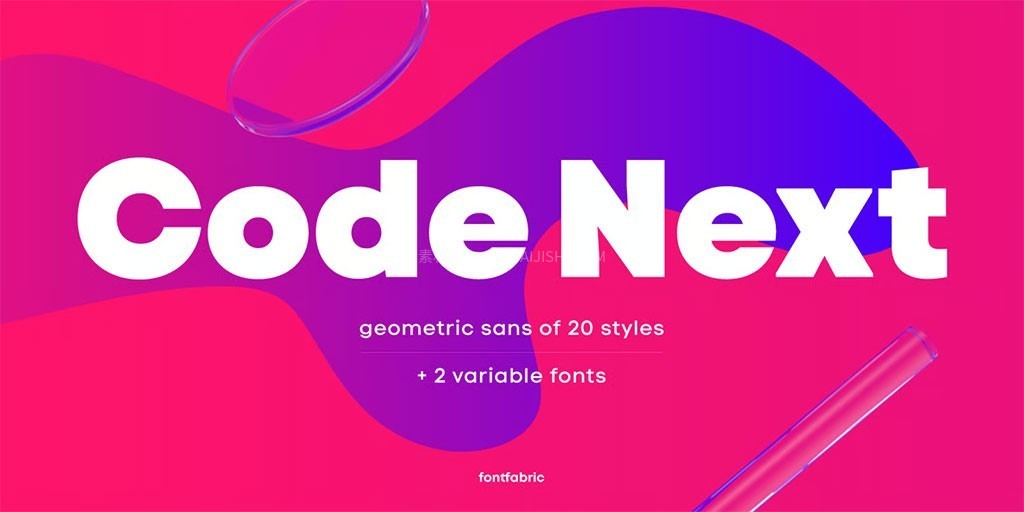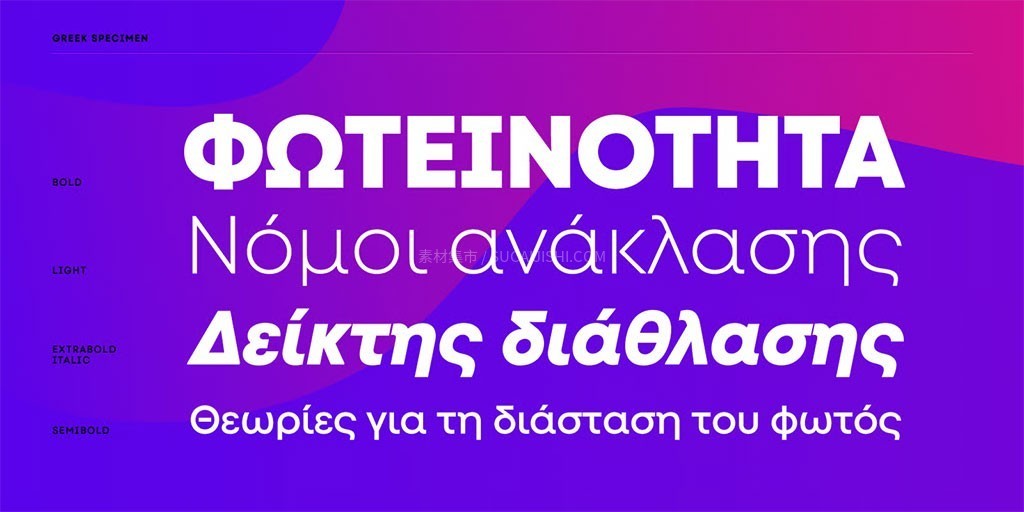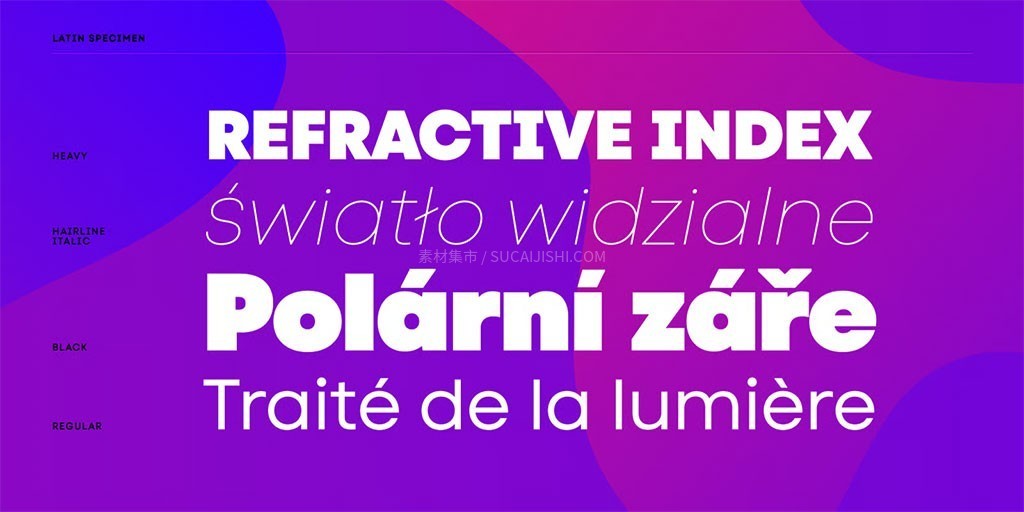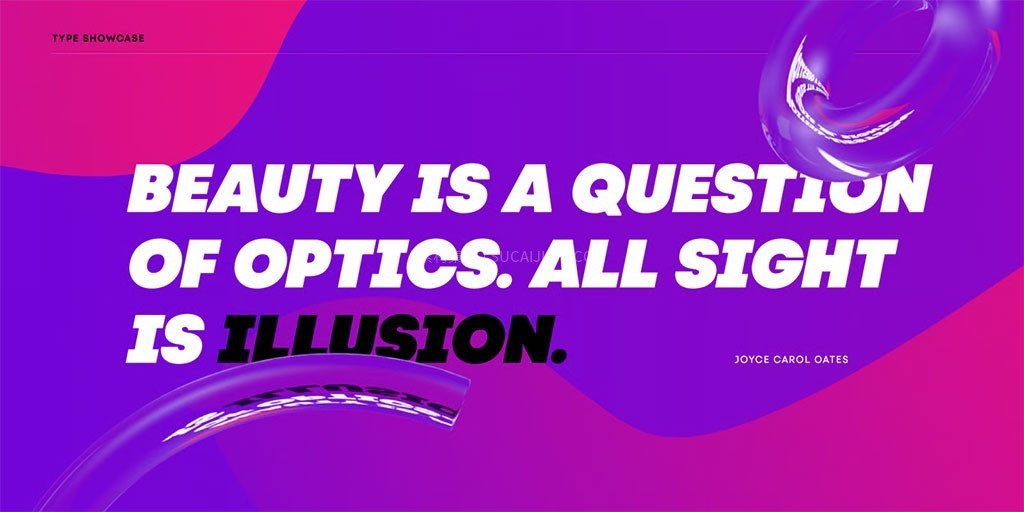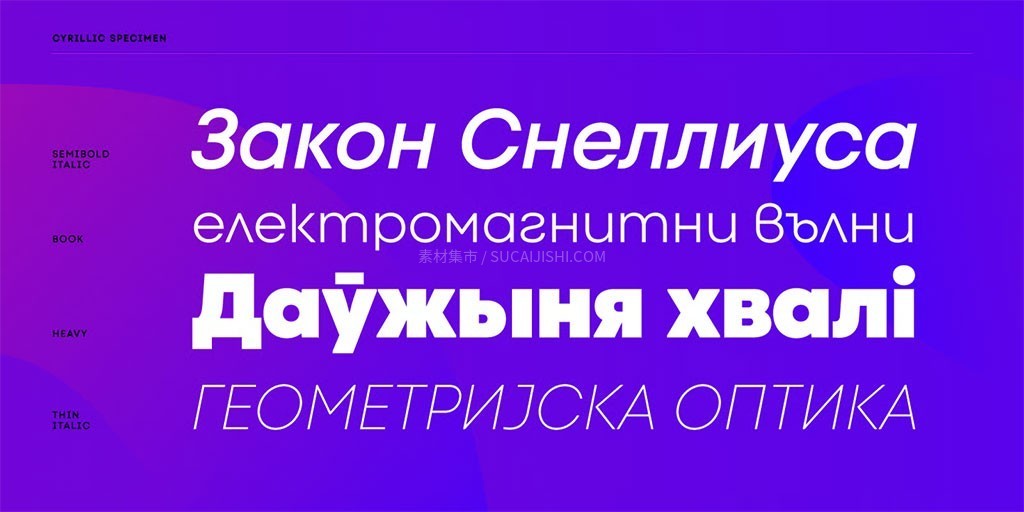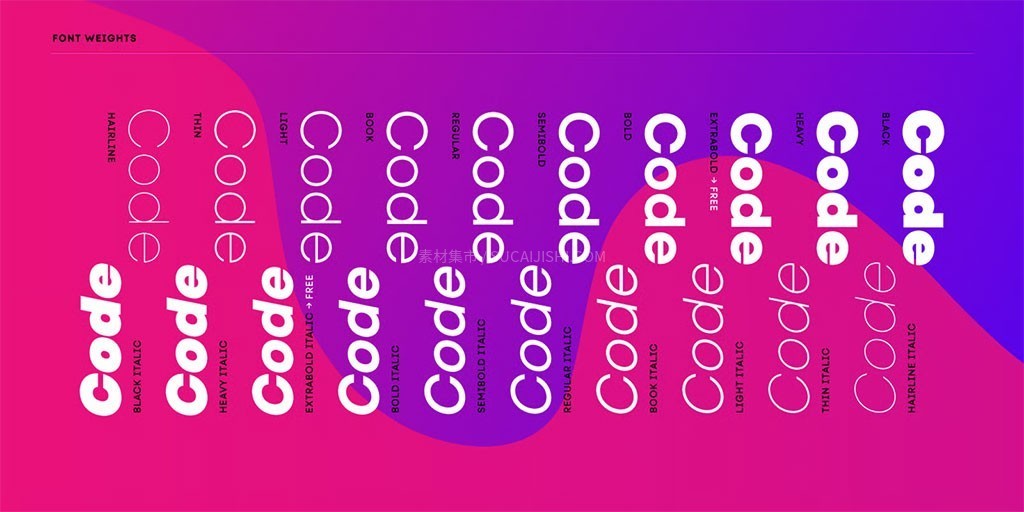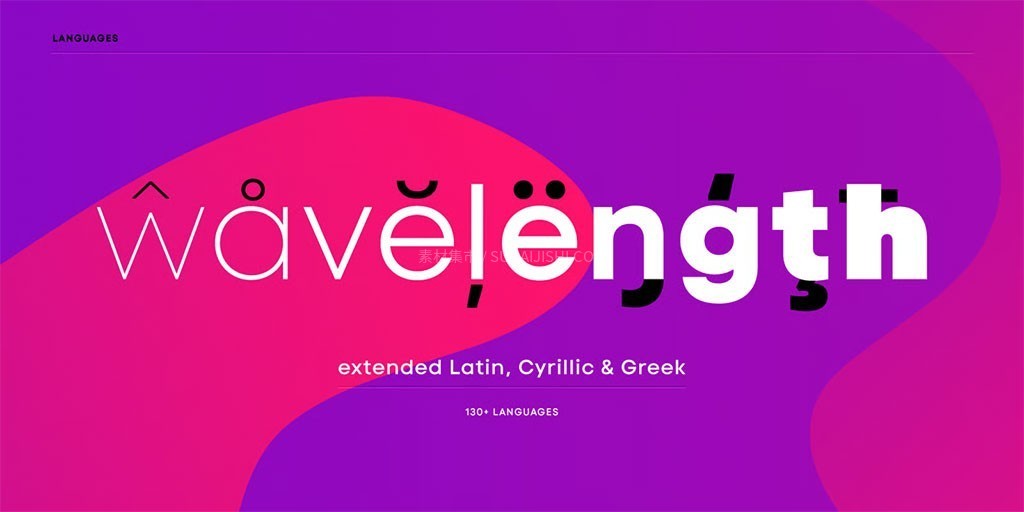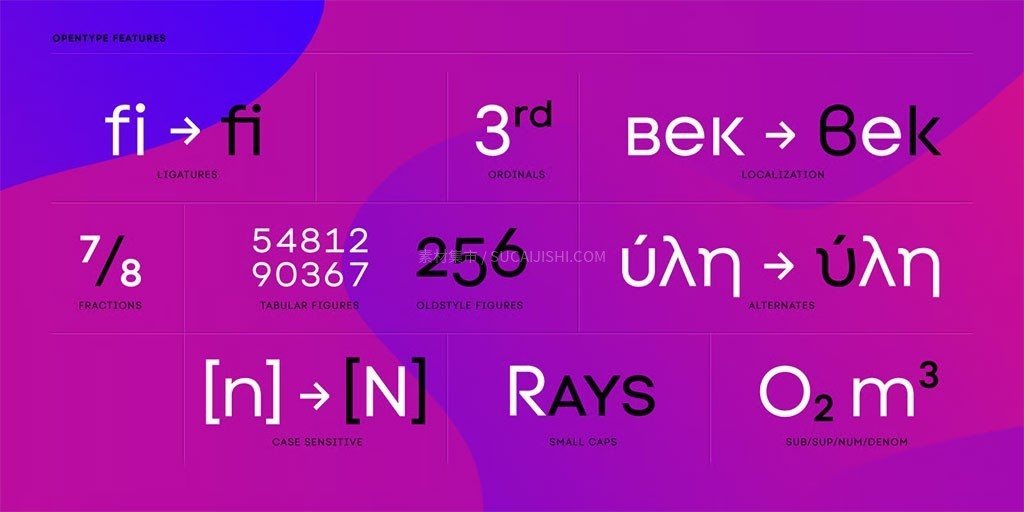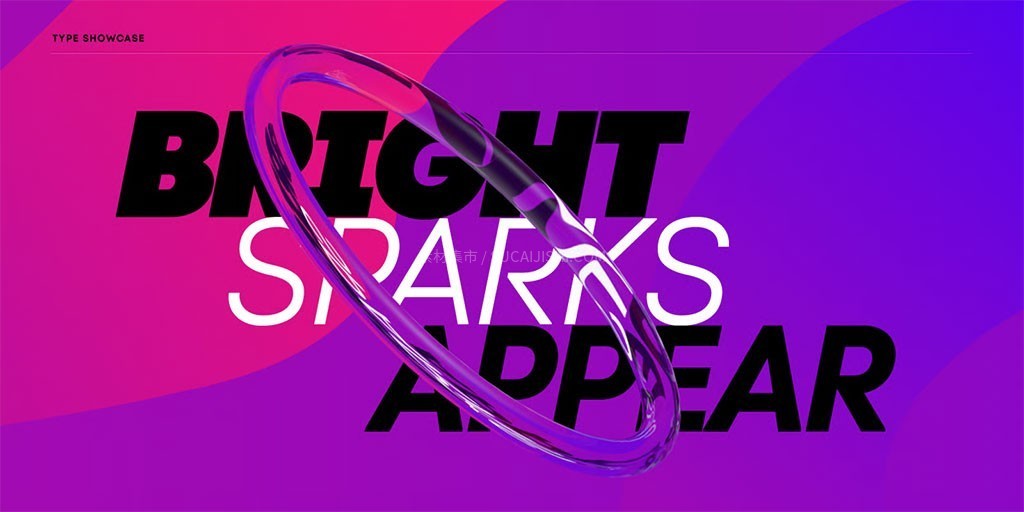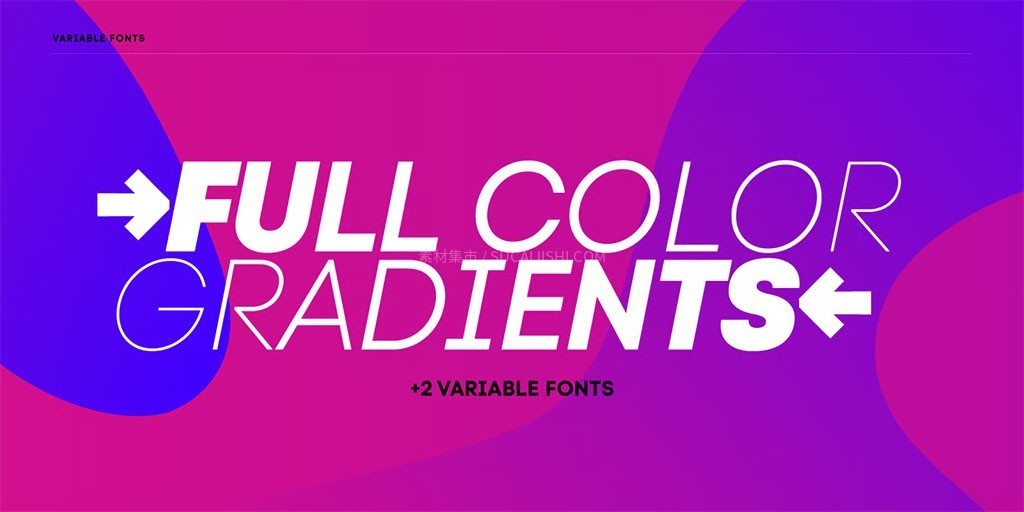
Code Next 完整系列字体
Code Next 是由 Fontfabric 团队精心打造的现代几何无衬线字体(原 Code Pro 升级版),全套包含 20 款静态字体与 2 款可变字体。该字体以简洁流畅的线条和独特的“扭曲”效果为特色,内置多达 1280+ 字形,并具备小型大写字母、连字、替代字形等丰富的高级 OpenType 功能。凭借其强大的多语言支持(扩展拉丁文、西里尔文、希腊文)与出色的灵活性,它能帮助您轻松构建清晰的排版层级,实现兼具前瞻性与高品质的视觉表达。